CSS fonts (CSS 폰트)
올바른 글꼴을 선택하는 것은 독자들이 웹사이트를 경험하는 방법에 큰 영향을 미찬다.
올바른 글꼴은 브랜드에 대한 강력한 아이덴티티를 만들 수 있다.
읽기 쉬운 글꼴을 사용하는 것은 중요하다. 글꼴은 텍스트에 값을 추가한다. 글꼴에 맞는 색과 텍스트 크기를 선택하는 것도 중요하다.
일반 글꼴 패밀리
CSS에는 5개의 일반 글꼴 계열이 있다:
- Serif 글꼴은 각 문자의 가장자리에 작은 획이 있다. 그들은 격식과 우아함을 만들어낸다.
- San-serif 글꼴은 줄이 깨끗하다(작은 획이 부착되지 않음). 그들은 현대적이고 미니멀리즘적인 모습을 연출한다.
- Monospace 글꼴 - 여기서 모든 문자는 동일한 고정 너비를 가진다. 그들은 기계적인 느낌을 준다.
- Cursive 글꼴은 사람의 필기체를 모방한다.
- Fantasy 글꼴은 장식적인/장난감 글꼴이다.
모든 다른 글꼴 이름은 일반 글꼴 패밀리 중 하나에 속합니다.
Serif와 Sans-serif 글꼴 차이
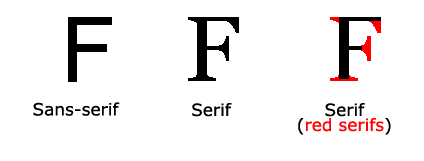
CSS font-family 속성
CSS에서는 font-family 속성을 사용하여 텍스트의 글꼴을 지정한다.
참고: 글꼴 이름이 두 단어 이상이면 "Times New Roman"과 같이 따옴표로 묶어야 한다.
팁: 브라우저/운영 체제 간의 호환성을 극대화하려면 글꼴 패밀리 속성에 "fallback" 시스템으로 여러 글꼴 이름이 포함되어 있어야 한다. 원하는 글꼴로 시작하여 일반 패밀리로 끝난다(다른 글꼴을 사용할 수 없는 경우 브라우저가 일반 패밀리에서 유사한 글꼴을 선택할 수 있음). 글꼴 이름은 쉼표로 구분해야 한다. 다음 장에서 폴백 글꼴에 대해 자세히 살펴볼 것이다.
p1 클래스에 font-family에는 "Time New Roman" 글꼴을 설정하였다.
p2 클래스에 font-family에는 Arial 글꼴을 설정하였다.
p3 클래스에 font-family에는 "Lucida Console" 글꼴을 설정하였다.
p요소에 p1, p2, p3 클래스를 글꼴을 적용한 결과 화면은 아래 그림과 같다.
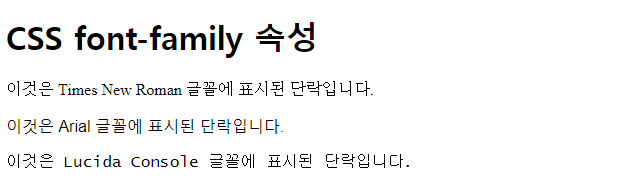
지금까지 CSS font-family 속성 예제와 CSS에서 폰트 활용에 대한 개념에 대해 살펴보았다.